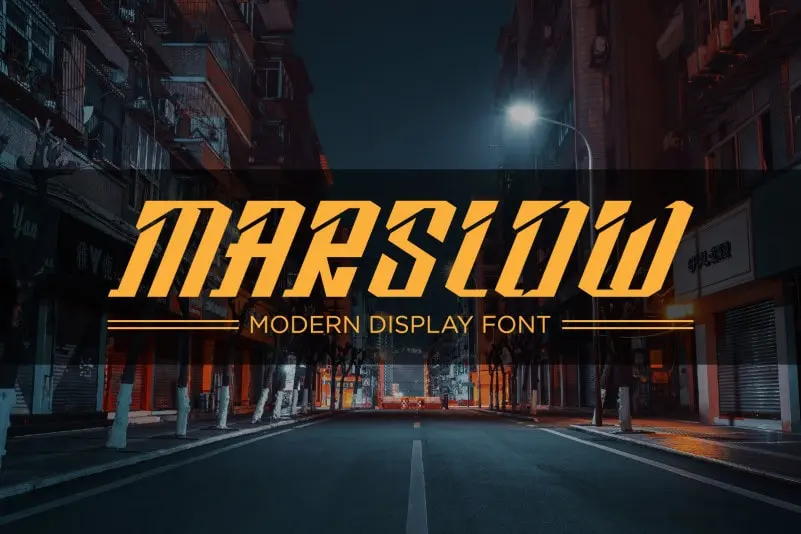
Marslow Font – Download Grátis
Esta é uma fonte chamada Marslow Font que oferece um visual atraente para ambientes decorativos. Seu design moderno e marcante fazê-lo destacar-se entre as demais, seja para uso nas criações relacionadas a temas como velocidade, potência ou esporte. Ideal tanto para aplicações digitais quanto impressivas, a fonte Marslow é uma excelente escolha para qualquer projeto em busca de um destaque único e inovador. Seja você designer web, gráfico ou editor de conteúdo, o Jprint Studio garante que esta font ofereça a versatilidade necessária para transformar seus projetos em verdadeiras obras de arte.
Designer: Jprint Studio